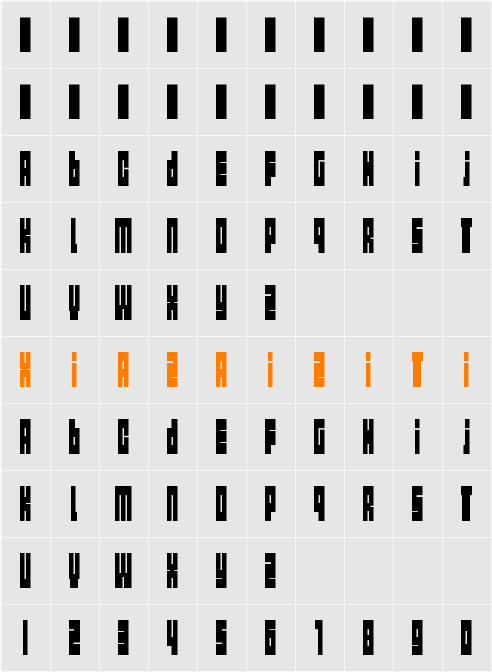
Yazo
Yazo,这款字体结构工整、笔画清晰,兼顾美观与易读性,适用于标题、正文、海报、包装、LOGO 等多种场景。字形优雅稳定,风格百搭耐看,适配日常排版与创意设计,让文字呈现更舒适、更具质感。Yazo一笔一画,皆是细节,以均衡的比例、流畅的线条打造舒适视觉体验,字形端正大气,风格简约现代。无论是商业设计、品牌宣传还是日常排版,都能轻松驾驭,让文字更有格调与力量。Yazo字体下载。